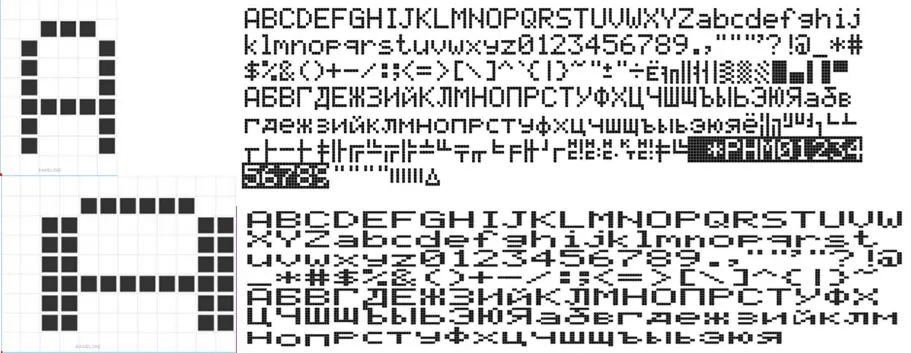
Шрифт ККМ ЭЛВЕС-ФР(ttf)
Шрифт кассового аппарата Элвес-ФР в формате TTF (русские и английские буквы) для использования в программе Microsoft Word. В архиве находятся шрифт в формате TTF и шаблон чека. Вам остается только установить шрифт в систему (обычно C:\WINDOWS\Fonts), открыть шаблон и начать редактирование. Печатать чеки предпочтительно на термопринтере, как, например, CITIZEN-S310, на кассовой термоленте. Хотя можно печатать и на струйнике и лазерном, с возможностью вывода на факсовую бумагу. Лучшее качество, естественно, при печати на термопринтерах.